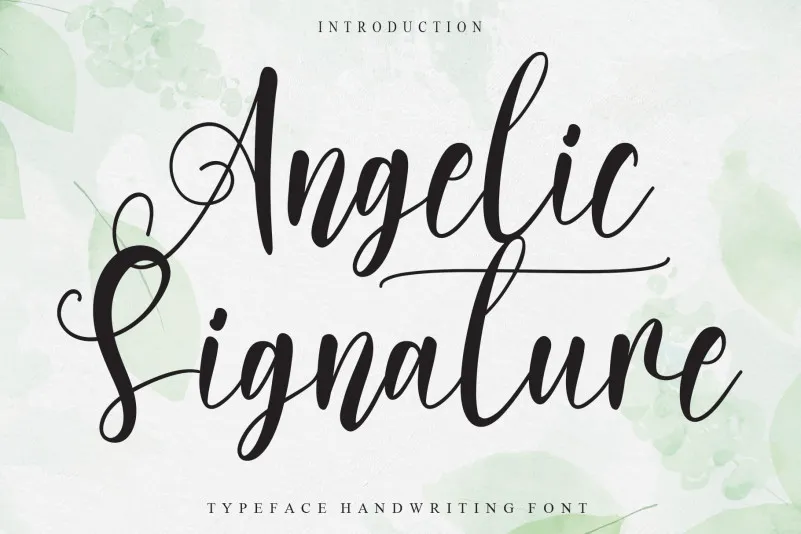
Angelic Signature Font – Download Grátis
Nossa fonte ‘Angelic Signature Font’ é uma elegante script que transmite sofisticação e luxo. Seu design refinado faz com que esteja perfeitamente adaptada para qualquer projeto, especialmente aqueles que buscam um toque de elegância. As alternativas estilizadas e ligaturas personalizadas a tornam o escolha ideal para quem busca uma combinação arrojada e sofisticada no seu trabalho. Se você está buscando um recurso gráfico para dar um toque diferenciado em sua próxima produção, esta fonte pode ser perfeita para complementar seus esboços de desenho, designs de logotipos ou qualquer projeto que exija uma personalização elegante e sofisticada. Experimente a ‘Angelic Signature Font’ e explore suas possibilidades incríveis.